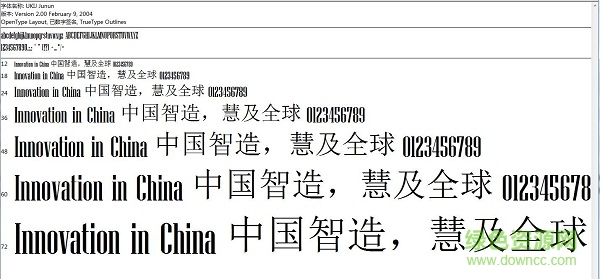
ukij junun
ukij junun字體是一款橫細(xì)豎粗的英文襯線字體,該字體豎線長(zhǎng),橫線短,字母間距小,筆畫(huà)密集,給人一種非常緊湊的感覺(jué),有需要者快來(lái)下載吧!
常見(jiàn)的襯線字體
過(guò)渡襯線體(Transitional)又稱巴洛克體:Times Roman、Baskerville
現(xiàn)代襯線體(Modern):Didot、Bodoni 、Century、Computer Modern
ukij junun字體